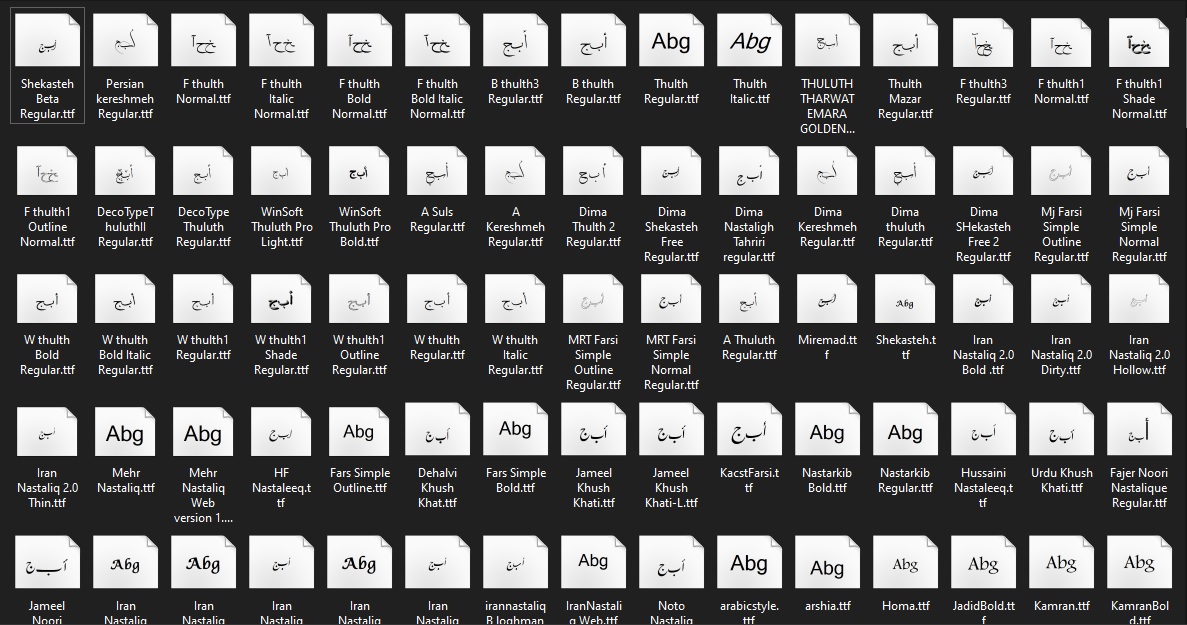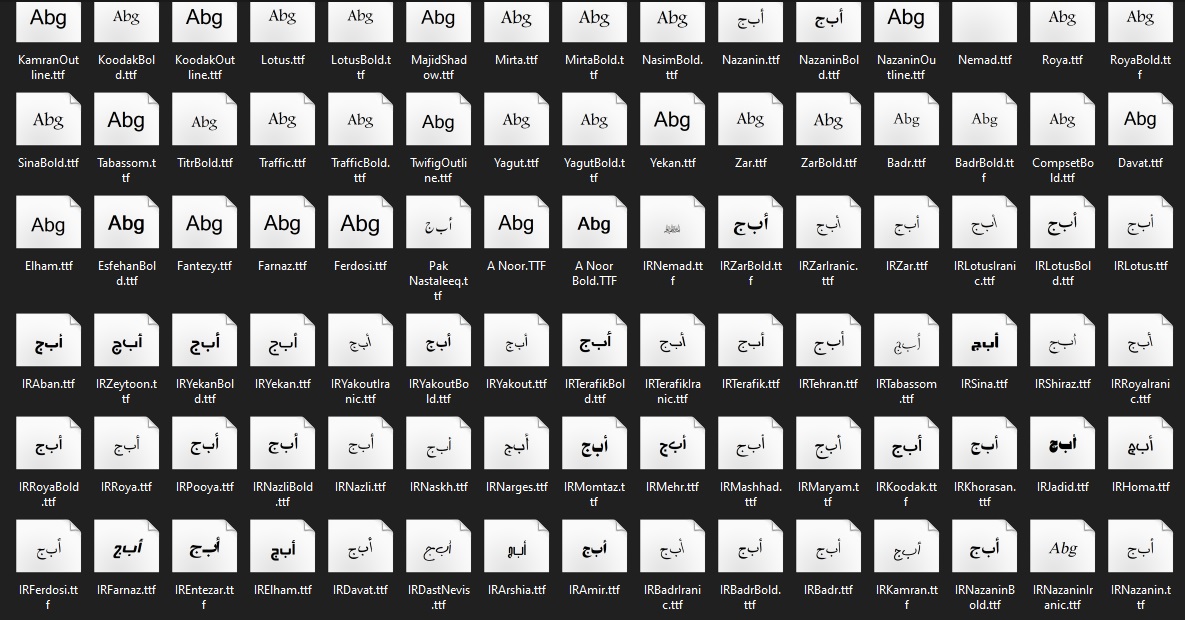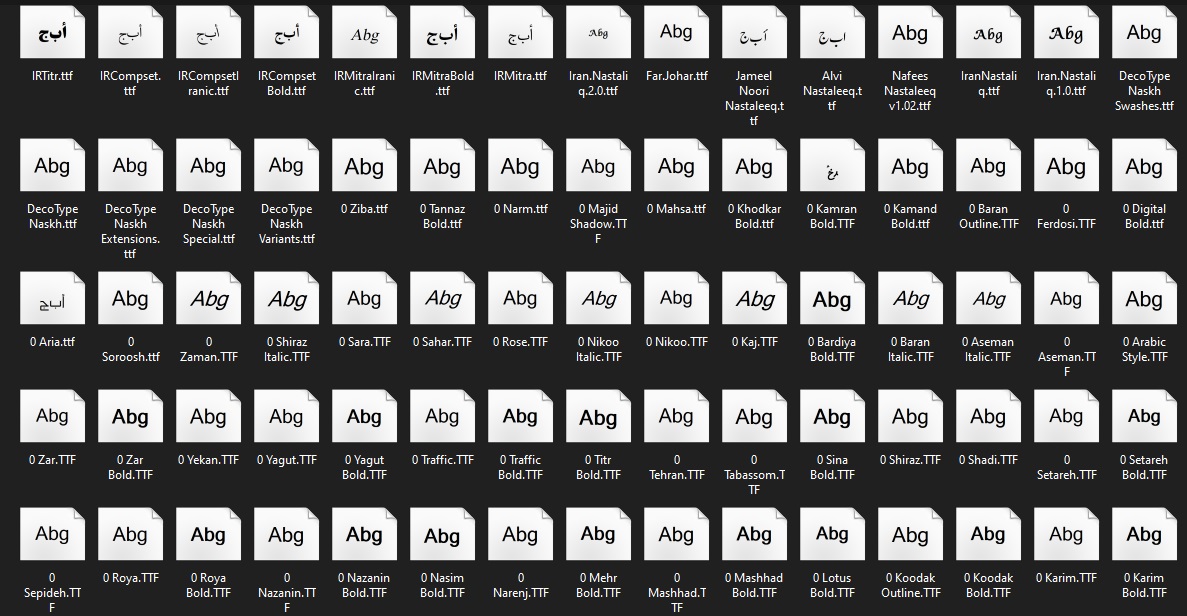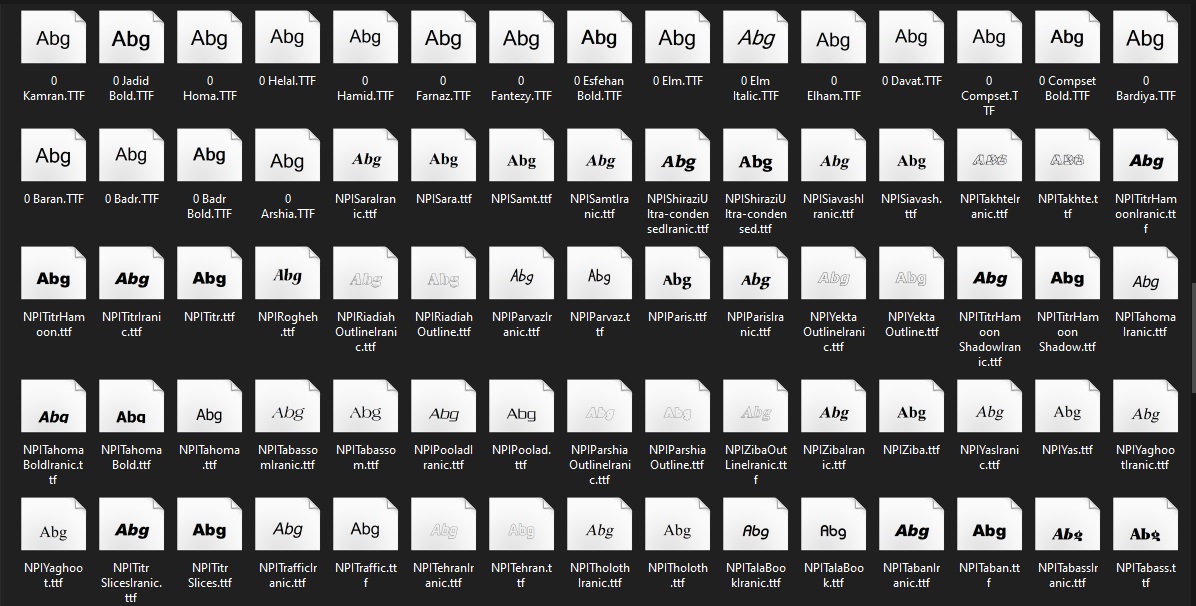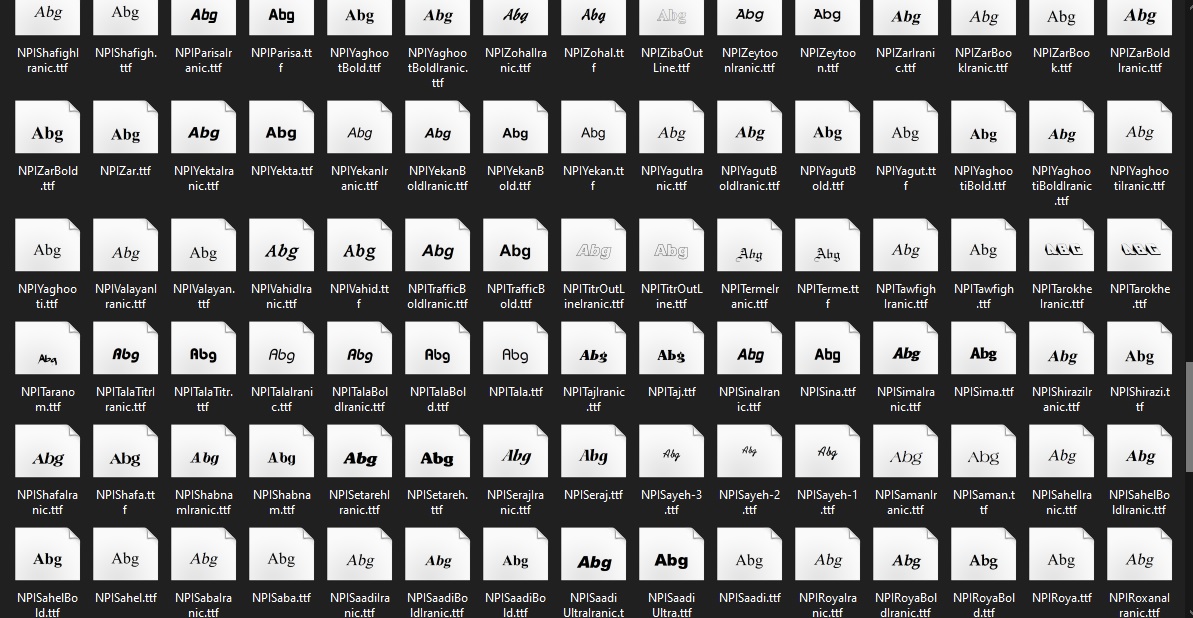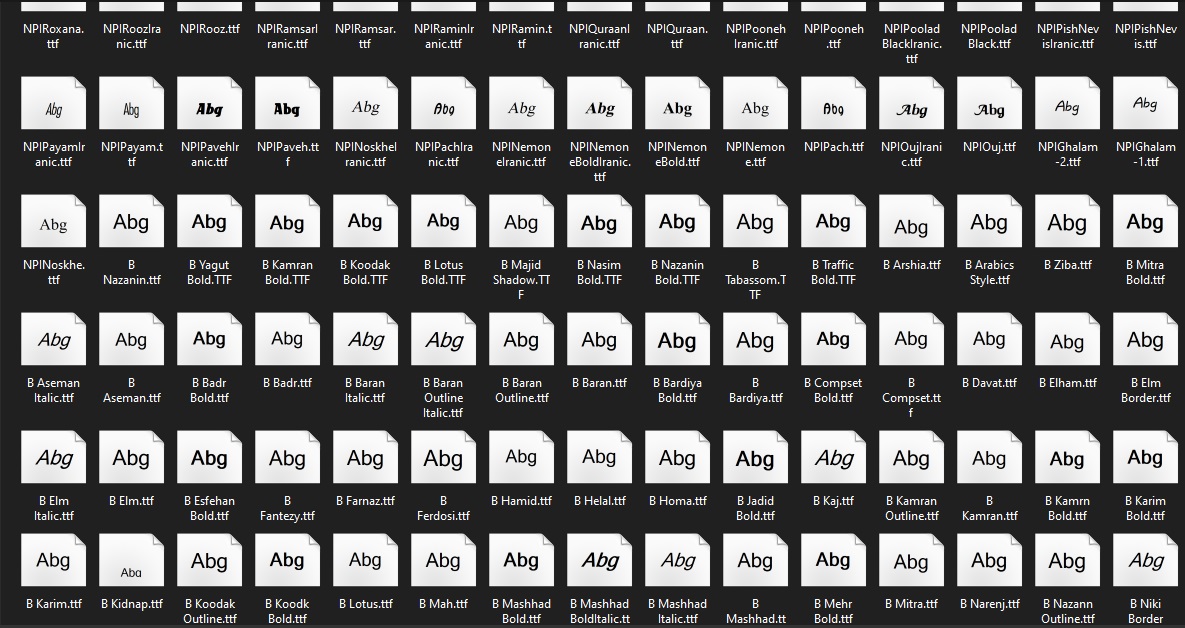
مجموعه +527 فونت فارسی
مجموعه ۵۲۷ فونت فارسی، یک آرشیو رایگان و جامع از قلم های فارسی است که به صورت یک فایل فشرده برای کاربران فراهم شده است. این مجموعه شامل طیف وسیعی از فونت ها با سبک ها و وزن های مختلف، از جمله فونت های محبوب و کاربردی مانند B Titr Bold، B Nazanin، B Roya، B Yekan، و انواع فونت های نستعلیق و شکسته مجموعه کامل فونت B و فونت F و فونت 0 و فونت W و… است. با فرمت TTF، این فونت ها برای استفاده در ویندوز، اندروید و iOS مناسب بوده و نیازهای متنوع کاربران را در طراحی گرافیکی، نشر، وب و کاربردهای روزمره برطرف می سازند. این مجموعه، دسترسی آسانی به صدها قلم فارسی را برای هر پروژه ای فراهم می کند.
مجموعه 527 فونت فارسی: آرشیو رایگان و جامع برای طراحان و کاربران
مجموعه ۵۲۷ فونت فارسی یک گنجینه رایگان و بی نظیر برای هر کسی است که با زبان فارسی در محیط های دیجیتال سروکار دارد. این آرشیو وسیع، شامل صدها قلم متنوع فارسی است که از فونت های رسمی و سنتی گرفته تا قلم های مدرن و فانتزی را در بر می گیرد و به صورت یک فایل فشرده برای دانلود رایگان آماده شده است. این مجموعه، نیاز به جستجوی تک تک فونت ها را از بین می برد و یکجا طیف گسترده ای از انتخاب ها را در اختیار شما قرار می دهد.
دانلوداین آرشیو با تمرکز بر نیازهای کاربران فارسی زبان، انواع مختلفی از قلم ها را پوشش می دهد:
- فونت های متنی و رسمی: مانند B Nazanin، B Roya، B Mitra و B Zar که برای نگارش متون طولانی، مقالات، پایان نامه ها و اسناد رسمی ایده آل هستند و خوانایی بالایی دارند.
- فونت های نمایشی و عنوانی: شامل قلم هایی مانند B Titr Bold، B Koodak Bold و B Sina Bold که برای عناوین اصلی، تیترها، طراحی پوسترها و تبلیغات بسیار مناسب بوده و جلوه ای چشم نواز به کار می بخشند.
- فونت های خاص و هنری: از جمله فونت های نستعلیق (مانند Iran Nastaliq) و شکسته (مانند Shekasteh) که برای طراحی های هنری، خوشنویسی دیجیتال و ایجاد حس و حالی سنتی و اصیل به کار می روند.
- فونت های مدرن و فانتزی: که برای طراحی های خلاقانه، لوگوها و برندسازی های نوین می توانند مورد استفاده قرار گیرند.
کاربردهای مجموعه فونت های فارسی در طراحی و نشر
مجموعه ۵۲۷ فونت فارسی با تنوع بی نظیر خود، طیف گسترده ای از کاربردها را در حوزه های مختلف طراحی گرافیک، نشر، وب و تولید محتوا فراهم می کند. این آرشیو جامع، به طراحان و تولیدکنندگان محتوا امکان می دهد تا برای هر پروژه و با هر سلیقه ای، فونت مناسب را انتخاب کنند.
این فونت ها برای متون اصلی در کتاب ها، مجلات، روزنامه ها و اسناد چاپی بسیار مناسب هستند، زیرا شامل قلم هایی با خوانایی بالا برای ساعات طولانی مطالعه می باشند. همچنین برای عناوین، تیترها، طراحی پوسترها و بنرهای تبلیغاتی می توان از فونت های نمایشی و بولد موجود در این مجموعه استفاده کرد تا تأثیر بصری قوی ایجاد شود.
دانلوددر حوزه دیجیتال و وب، این فونت ها برای طراحی وبسایت ها و رابط های کاربری (UI)، به خصوص در بخش های متنی و عنوانی، کارایی زیادی دارند. در شبکه های اجتماعی نیز، این فونت ها می توانند برای ساخت عکس نوشته های جذاب و استوری های خلاقانه مورد استفاده قرار گیرند. علاوه بر این، این مجموعه شامل فونت هایی با سبک های سنتی و هنری است که برای خوشنویسی دیجیتال، طراحی لوگو با حس اصیل ایرانی و سایر پروژه های هنری بسیار کاربردی می باشند. دسترسی به این حجم عظیم از فونت های رایگان، آزادی عمل بی سابقه ای را در خلق طرح های متنوع و چشم نواز به ارمغان می آورد.
مجموعه ۵۲۷ فونت فارسی در فرمت TTF عرضه شده است که یکی از رایج ترین فرمت های فونت بوده و سازگاری بالایی با انواع سیستم عامل ها و نرم افزارهای کاربردی دارد. این فونت ها قابل استفاده در تمام نرم افزارهایی که یونیکد را پشتیبانی میکنند و همچنین در تمام نرم افزارهایی که از زبان های راست به چپ پشتیبانی میکنند، از جمله نرم افزارهای حرفه ای طراحی گرافیک (مانند فتوشاپ، ایلاستریتور، کورل دراو) و نرم افزارهای ویرایش متن (مانند مایکروسافت ورد) یا در موبایل مثل اینشات ، پیکس آرت ، اینستاگرام و … می باشند. این فونت ها از تایپ مستقیم پشتیبانی می کنند.